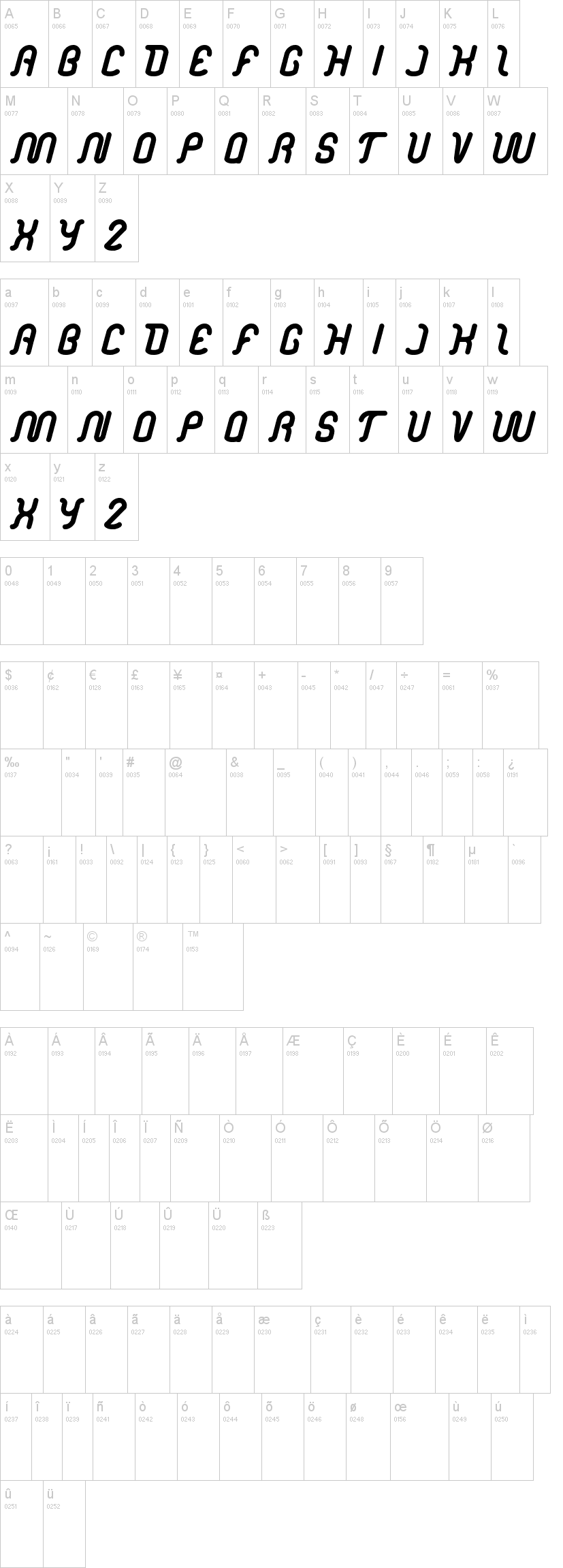
Electronic
Electronic 字体是一种现代风格的电子字体,它具有独特的外观,可以提供更加现代化的设计灵感。它有着简洁的线条,更加精细的细节,可以提供多种不同的外观效果。它也可以用于创造出更加复杂的设计,比如文字的细节和图形的细节。另外,它也可以用于创建出更多的动态效果,比如动态文字或图形。
Electronic是一款非常不错的手写艺术字体,具有很好的视觉感,适合于文化类的宣传设计、商业类品牌的广告和产品包装设计以及个性化文字排版等较多场景。
Electronic字符映射图